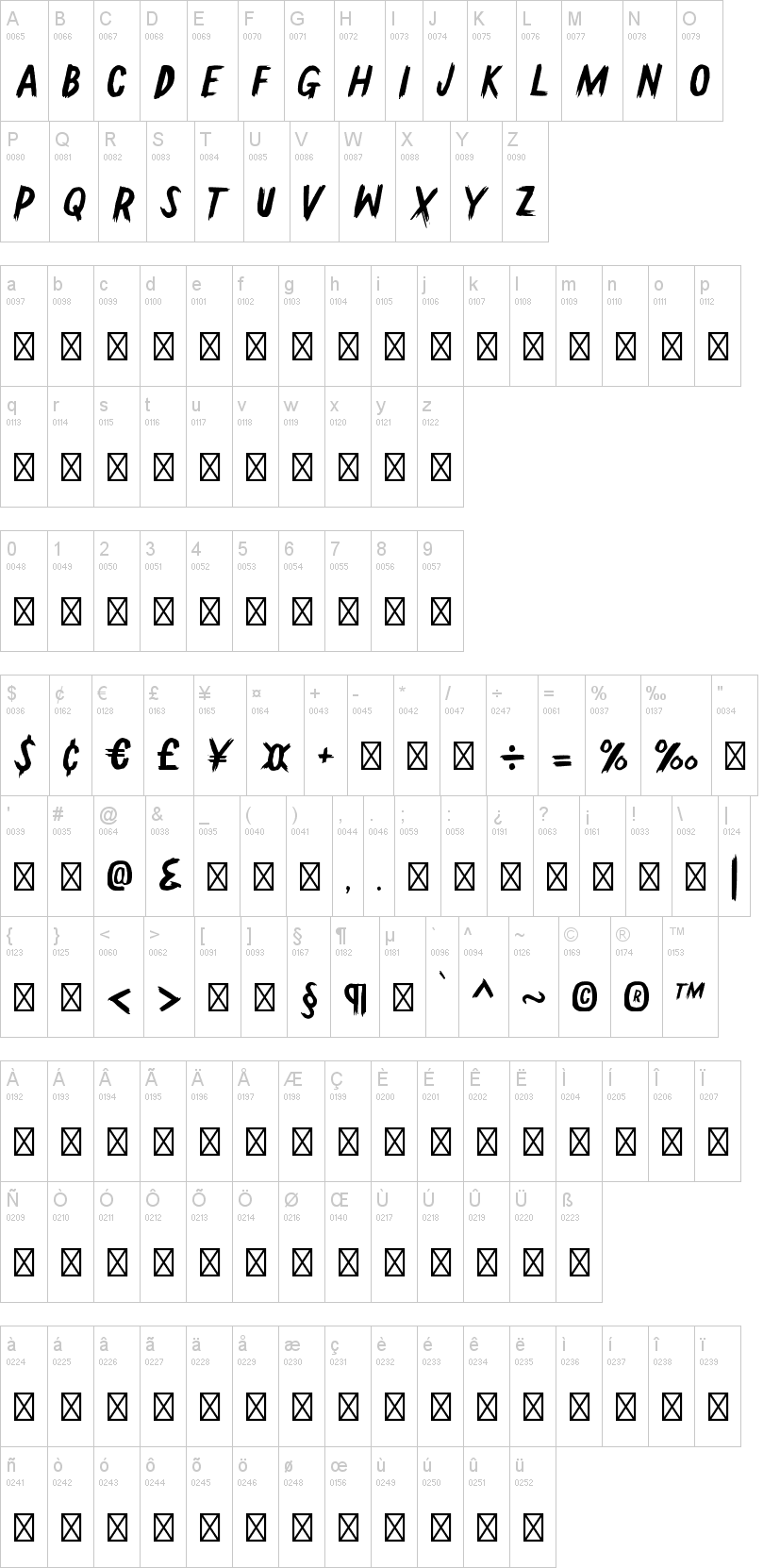
Gallow Tree
Gallow Tree 是一种手写风格的字体,通常用于标题、海报、书籍封面等需要强调视觉效果的设计中。 这种字体的特点是笔画粗细不一,有些笔画甚至呈现出“断掉”的效果,让字体看起来更加生动有趣。同时, Gallow Tree 字体的字母间距较大,让整个文本更加易读。 Gallow Tree 字体有多种版本,包括常规、加粗和斜体等。它常用于表达蓬勃向上、自由灵动或者是神秘诡异等特定的情感或氛围。
Gallow Tree是一款非常不错的手写艺术字体,具有很好的视觉感,适合于文化类的宣传设计、商业类品牌的广告和产品包装设计以及个性化文字排版等较多场景。
Gallow Tree字符映射图